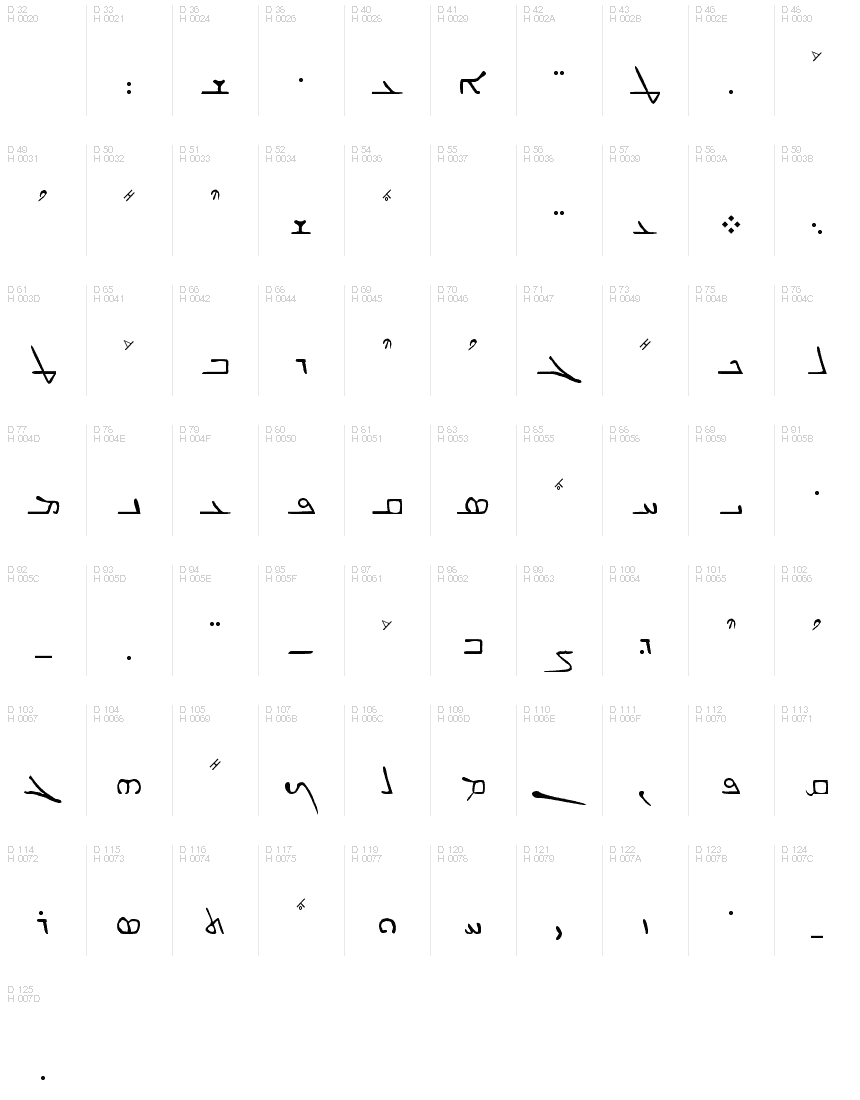
SP Edessa to darmowy font typu dingbats oparty na krojach Leiden Peshitta i Estrangela, czerpiący z zaokrąglonego, ręcznie kreślonego ducha syryjskiego pisma. Znaki te są jednocześnie ceremonialne i ludzkie – dzięki pętelkowym łukom, haczykowatym kreskom i zwartym kształtom nie sprawiają wrażenia neutralnych symboli, lecz raczej fragmentów wyjętych ze starej tradycji rękopiśmiennej.
Ten darmowy font sprawdzi się w projektach wymagających historycznego lub liturgicznego akcentu: na okładkach książek, w grafikach muzealnych, plakatach kulturalnych, kartach tytułowych czy krótkich nagłówkach. Świetnie nadaje się również do inicjałów lub znaków typu monogram, ponieważ litery mają na tyle dużo charakteru i rytualnego wyrazu, że z powodzeniem wypełnią niewielką przestrzeń jako samodzielne elementy.
based on Leiden Peshitta, Estrangela